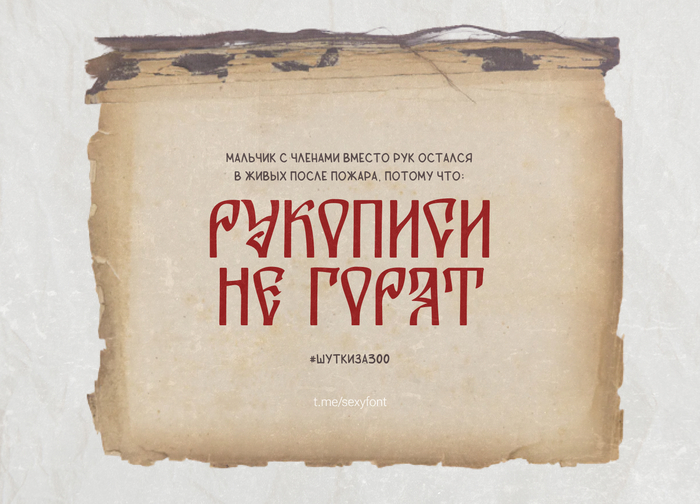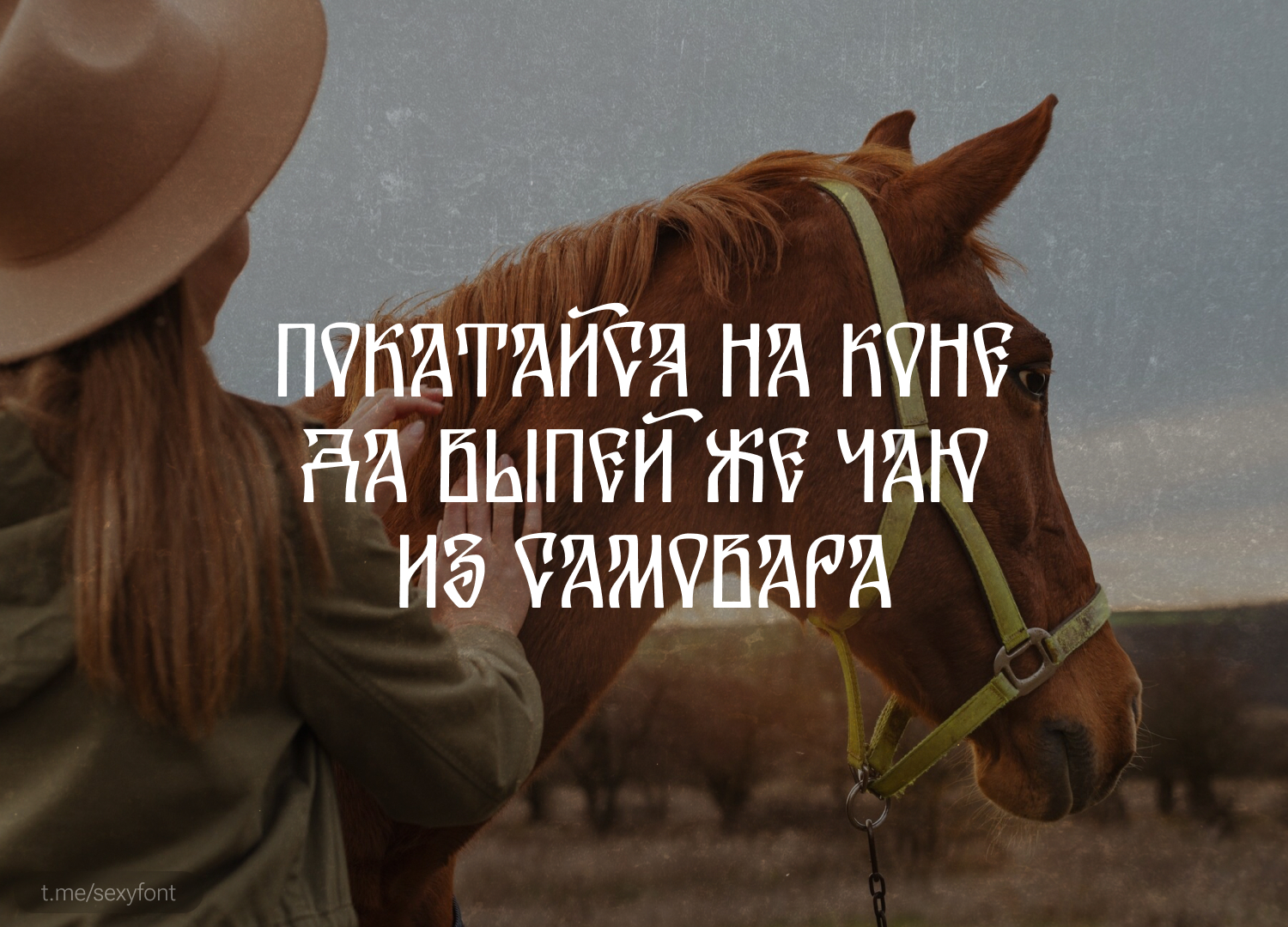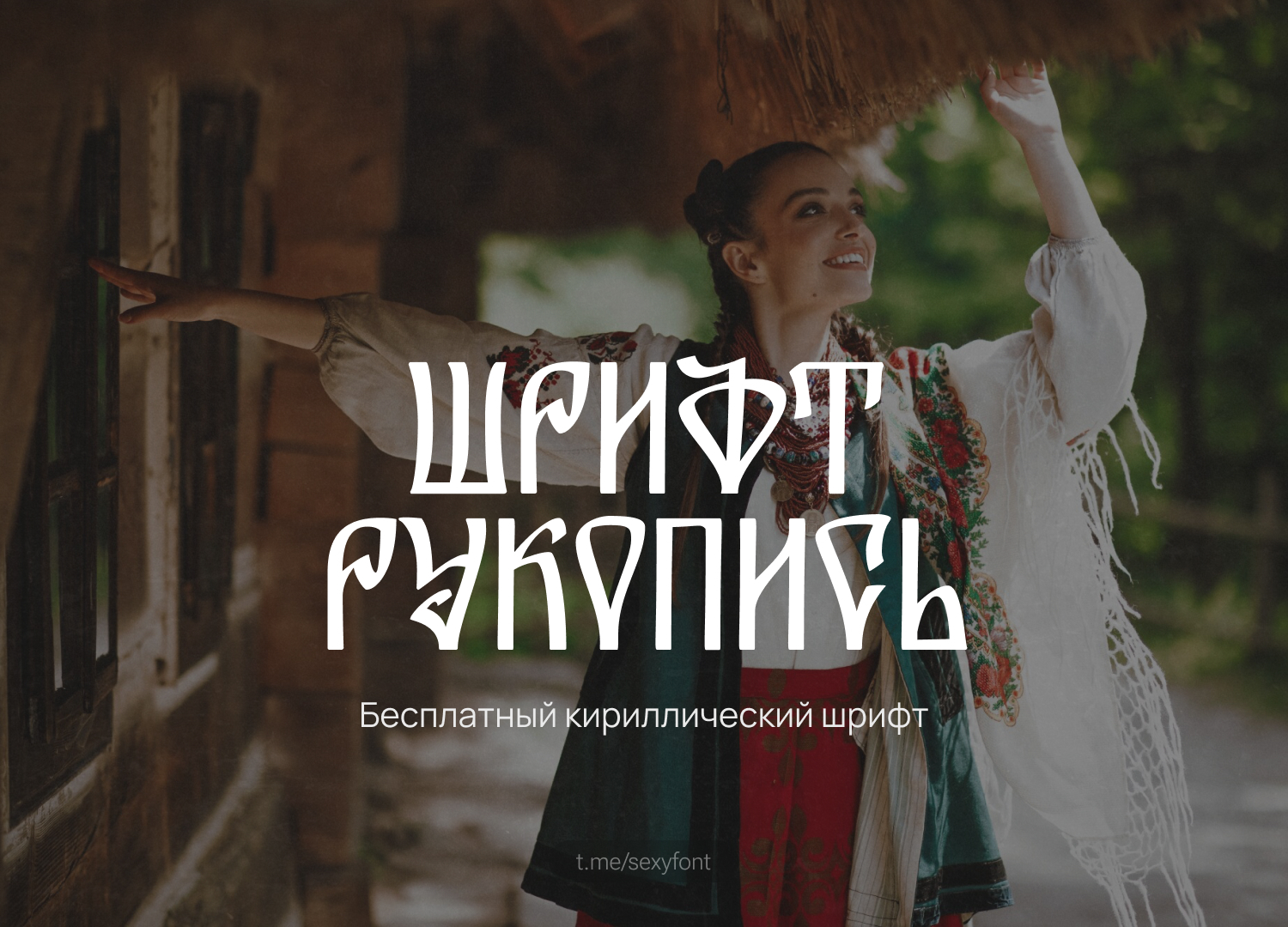
Бесплатный шрифт "Рукопись" Кириллица
Рукопись (Rukopis) Красивый, декоративный шрифт от Дмитрия. В его фирменной подаче. А презентация уже в моем стиле. (поддерживает только кириллицу)